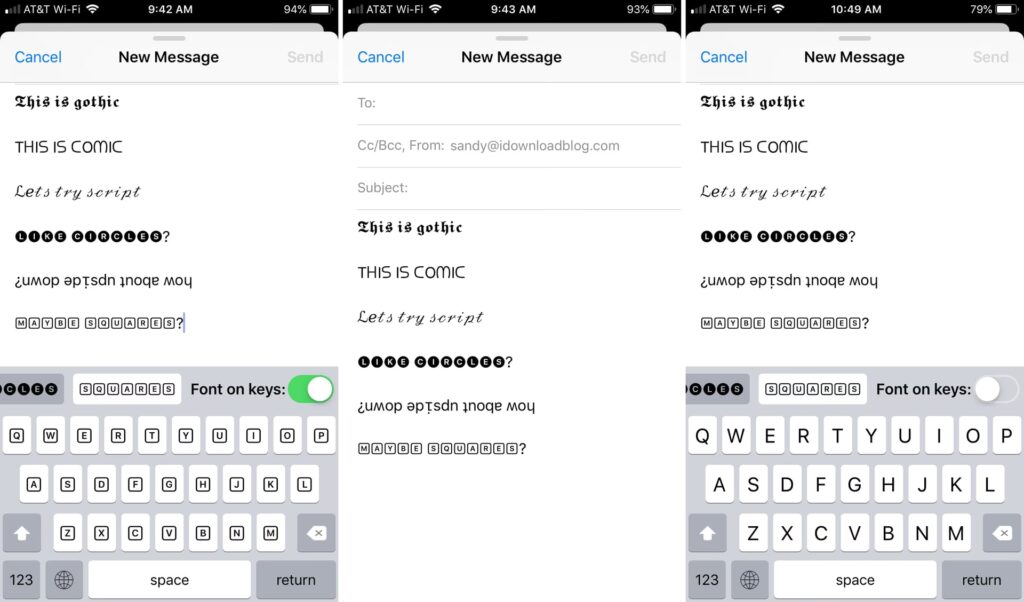
I en verden, hvor vores smartphones er blevet en forlængelse af os selv, er muligheden for at personliggøre dem mere efterspurgt end nogensinde. Selvom Android ofte fremhæves for sin åbne tilpasning, har iPhone også gjort store fremskridt. Fra automatiseringer til skærmovergange – der er utallige måder at gøre din iPhone unik på. Men hvad med et af de mindste, men mest virkningsfulde elementer: skrifttyperne? En velvalgt skrifttype kan forvandle en almindelig besked til et visuelt mesterværk og give din digitale kommunikation et helt nyt niveau af udtryk. Lad os dykke ned i de bedste skrifttype-tastaturer og apps, der kan hjælpe dig med at give din iPhone et frisk og personligt udseende.
Hvad er skrifttype-apps?
Før vi kaster os ud i de bedste iOS-skrifttype-applikationer, lad os kort definere, hvad skrifttype-apps faktisk er. App Store er et kæmpe univers fyldt med millioner af programmer designet til at opfylde forskellige funktioner, og skrifttype-apps er ingen undtagelse. Disse apps giver brugere mulighed for at ændre skrifttypen på deres mobile enheder ved at tilbyde et bredt udvalg af skrifttypevalg og tilpasningsværktøjer. Med disse apps kan du potentielt ændre skrifttypen for en enkelt applikation eller endda hele systemet, afhængigt af appens funktionalitet og iOS-begrænsninger. Mange skrifttype-apps inkluderer både gratis og premium skrifttyper, hvor de betalte ofte tilbyder mere unikke og konfigurerbare muligheder. Udover at give brugere mulighed for at ændre tekstens størrelse og farve, inkluderer mange skrifttype-apps også ekstra funktioner såsom teksteffekter og baggrunde, hvilket giver en endnu dybere tilpasning. Selvom skrifttype-applikationer kan være en sjov måde at ændre udseendet af din mobile enhed på, er det vigtigt at huske, at ikke alle skrifttyper er kompatible med alle apps og enheder. Derudover er specifikke skrifttyper muligvis ikke optimeret for læsbarhed eller tilgængelighed, så det er afgørende at vælge skrifttyper, der er lette at læse og bruge. Det er også klogt at udvise forsigtighed, når du downloader skrifttyper fra tredjepartswebsteder, da de kan indeholde malware og andre sikkerhedstrusler. Hold dig til anerkendte apps fra App Store.
Hvorfor ændre standard skrifttypen på din iPhone?
Når vi taler om skrifttype-apps, spørger de fleste mennesker: Er det nødvendigt at ændre min standard skrifttype? Det ligefremme svar er nej. At ændre skrifttypestil og -størrelse er helt op til den enkeltes valg. Men du har sikkert bemærket, at skrifttypestilen gør en stor forskel i udseendet, uanset om det er et dokument, Instagram-historier eller en bio. De fleste bruger forskellige skrifttypestile for at gøre deres bio eller historie attraktive og skille sig ud. Samlet set kan vi sige, at det ikke er nødvendigt at ændre skrifttyper. Men du kan stadig prøve at bruge dem for en bedre visning og udseende. At ændre standard skrifttypen på din iPhone kan give flere fordele, som vi diskuterer nedenfor:
Forbedret læsbarhed
Nogle skrifttyper er mere læselige og lettere at læse end andre, især for synshandicappede. Ved at ændre standard skrifttypen på din iPhone kan du vælge en skrifttype, der er mere læsbar og behagelig for dig at bruge. Dette kan være afgørende for at mindske øjenbelastning og forbedre din generelle brugeroplevelse.
Personliggørelse
At ændre standard skrifttypen på din iPhone kan hjælpe dig med at personliggøre din enhed og få den til at føles mere som din egen. Du kan vælge en skrifttype, der afspejler din stil eller personlighed, eller skifte til en anden skrifttype for en forandring. Det handler om at udtrykke din individualitet gennem din digitale platform.
Tilgængelighed
At ændre skrifttypen på din iPhone kan også gøre den mere tilgængelig for personer med synshandicap eller ordblindhed. Nogle skrifttyper er specifikt designet til at være mere tilgængelige, med større, klarere bogstaver og forbedret afstand mellem bogstaver og ord. Dette er en vigtig funktion for at gøre teknologi mere inklusiv.
Forbedret fokus
Nogle skrifttyper er mere beroligende eller lettere for øjnene end andre. Dette kan hjælpe med at reducere øjenbelastning og forbedre din evne til at fokusere. For eksempel betragtes skrifttyper som Helvetica eller Arial ofte som mere beroligende og lettere for øjnene end ornamenterede eller dekorative skrifttyper. En mindre distraherende skrifttype kan forbedre din koncentration.
Bedre produktivitet
At ændre standard skrifttypen på din iPhone kan forbedre din produktivitet og effektivitet, når du bruger din enhed. En skrifttype, der er lettere at læse og mindre distraherende, kan hjælpe dig med at holde fokus og udføre opgaver hurtigere og mere nøjagtigt. Det handler om at optimere din digitale arbejdsgang for maksimal effektivitet.
Samlet set kan ændring af standard skrifttypen på din iPhone hjælpe dig med at personliggøre din enhed, forbedre læsbarhed og tilgængelighed og øge din produktivitet og fokus. Med et bredt udvalg af skrifttyper at vælge imellem kan du finde en, der passer til dine behov og præferencer og forbedrer din samlede iPhone-oplevelse.
De bedste skrifttype-apps til iPhone
App Store er et stort univers fyldt med millioner af apps, og det er ikke let at finde den præcise app, der kan opfylde dine behov. Derfor har vi samlet nogle af de bedste skrifttype-apps til iPhones for at gøre det nemt for dig at vælge. Disse apps er udvalgt baseret på deres funktionalitet, brugervenlighed og evne til at levere de lovede tilpasningsmuligheder.
Smart Fonts: Font Keyboard
Er du træt af at drukne i mængden af almindelige billedtekster, biografier og historier på sociale medier? Smart Fonts-tastaturet giver dig mulighed for ubesværet at skille dig ud. Slip din kreativitet løs og gør et varigt indtryk på platforme som Instagram, hvor tilpasning er nøglen til at fange opmærksomhed. Smart Fonts: Font Keyboard tilbyder et omfattende udvalg af brugerdefinerede skrifttyper lige ved hånden, alle tilgængelige fra din iPhone. Forestil dig ubesværet at opnå topkommentarer på Instagram, YouTube, TikTok og mere ved at bruge unikke skrifttyper, der får dine kommentarer til at springe i øjnene. Med Smart Fonts har det aldrig været nemmere at skille sig ud i et overfyldt kommentarfelt. Tag kontrol over din online persona ved at bruge det brugerdefinerede skrifttype-tastatur problemfrit på tværs af alle dine iPhone-apps. Fra at dominere scenen på sociale medier til at udtrykke dig i e-mails, historier og videre, tilbyder Smart Fonts en universel løsning til dine tilpasningsbehov. Smart Fonts går ud over blot bogstaver. Løft dit spil på sociale medier ved at tilpasse dine navne med unikke skrifttyper og symboler. Skab et statement, der afspejler din individualitet, og sørg for, at din online tilstedeværelse er lige så særpræget som du er.